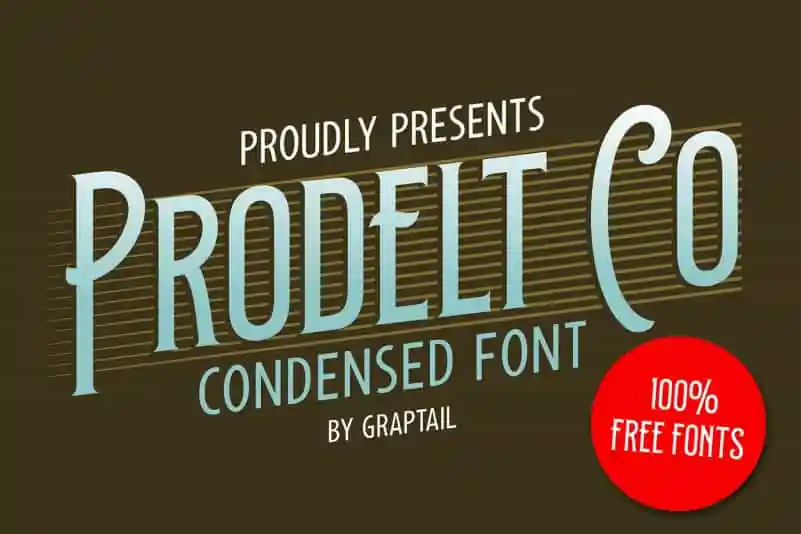
Prodelt Co Display Font – Download Grátis
Prodelt Co Display Font é uma tipografia para displays projetada pela Graptail Studio que combina estilos clássicos com contemporâneos. Inspirada na cultura urbana, essa fonte multipropósito traz caracteres atraentes e é adequada para diversos usos visuais, desde logotipos até postais. Suas alternativas ampliadas oferecem uma grande liberdade criativa, permitindo que designers desenvolvam soluções elegantes para headlines, logos, materiais de embalagem, adesivos em t-shirts e até cartazes. A Graptail Studio apresenta à fonte um estilo retrô, inspirado nos rótulos clássicos usados nas embalagens de produtos modernos, proporcionando uma paleta vibrante que reflete tanto os detalhes quanto as cores da tipografia em diferentes formatos de letras. Como parte desta combinação dinâmica e versátil, Prodelt Co Display Font é uma escolha perfeita para quem busca um visual inovador para trabalhos visuais variados.